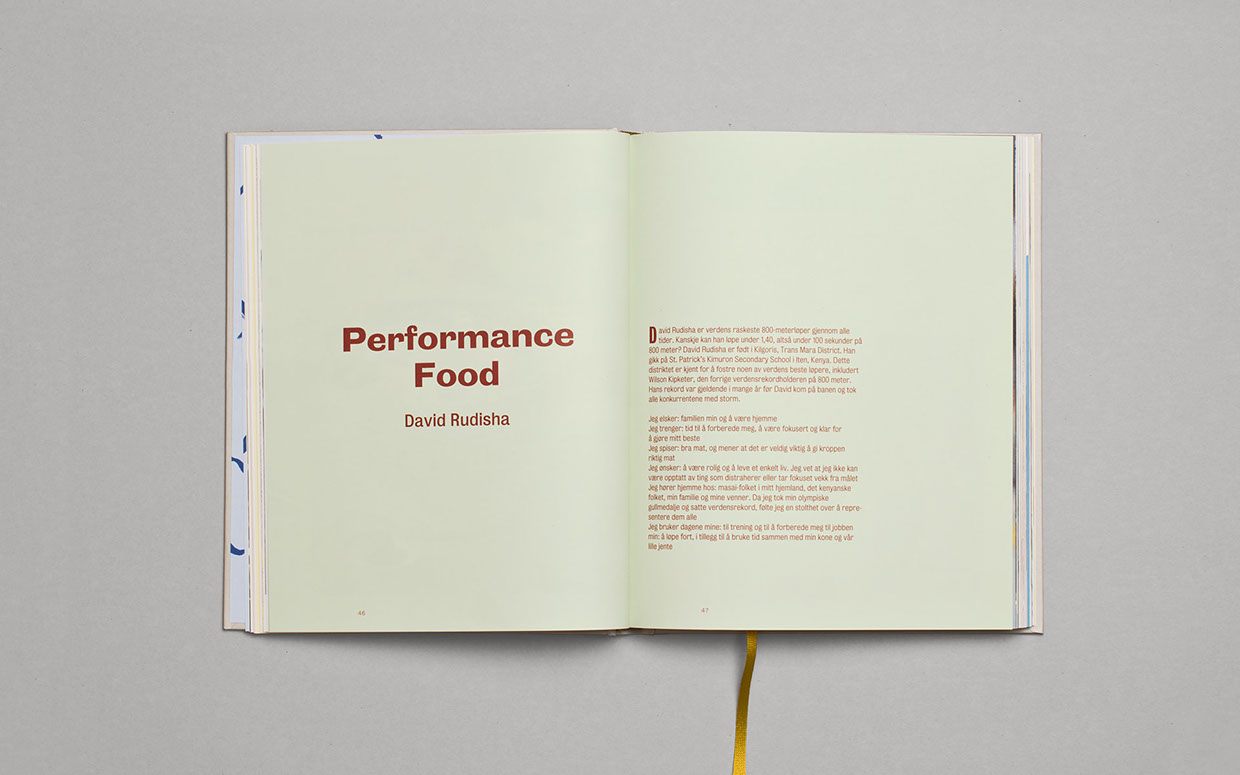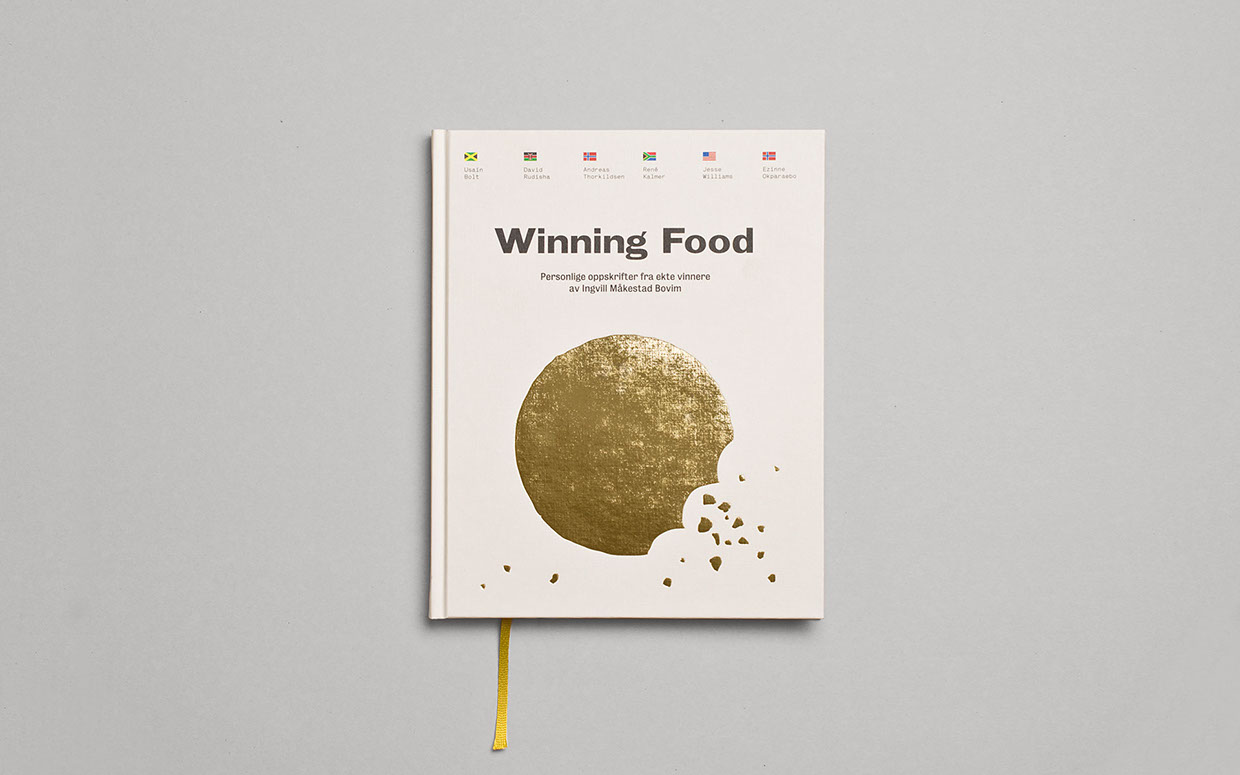
Schrift von Buch »Winning Food« gesucht
Buch »Winning Food«, geschrieben von Ingvild Måkestad Bovim
Weiß jemand spontan um welche statisch-amerikanische Grotesk mit mehreren Weiten es sich hier handelt? Ich komm’ nicht drauf …